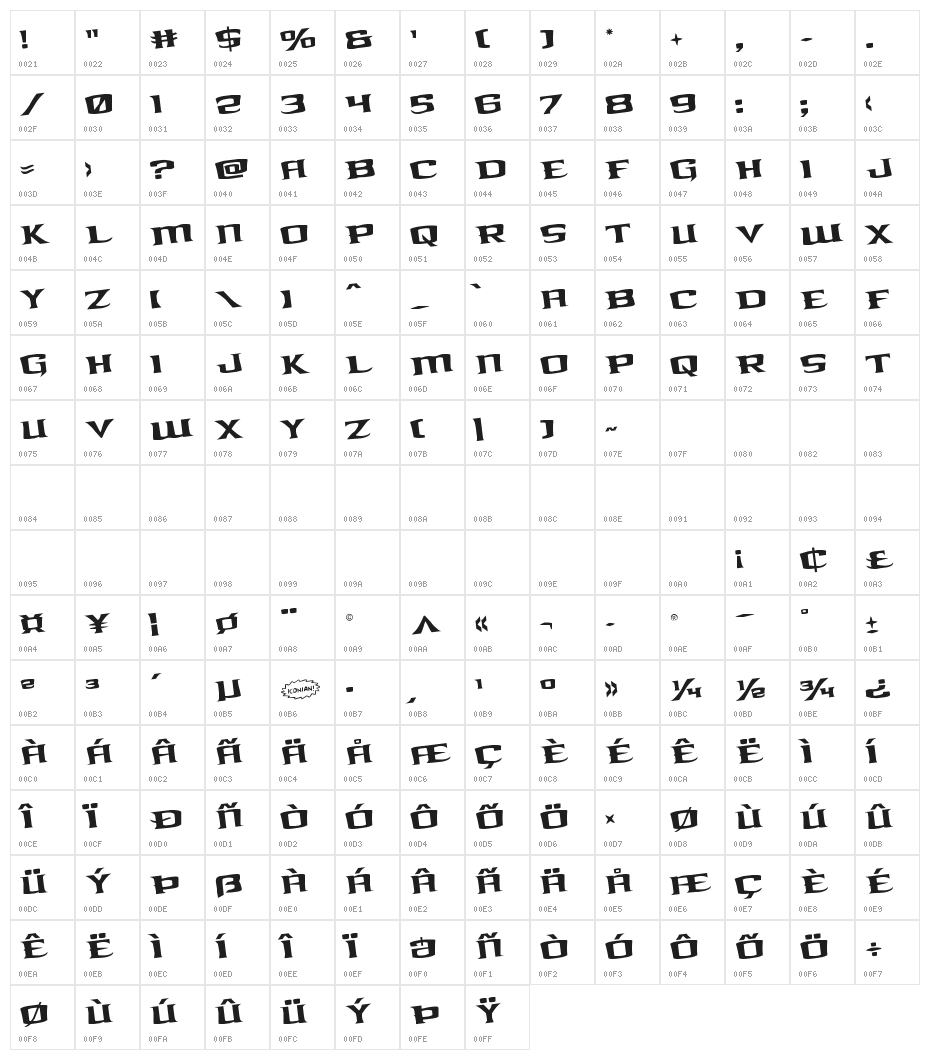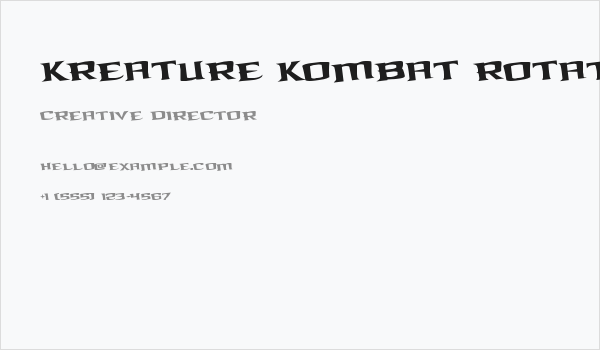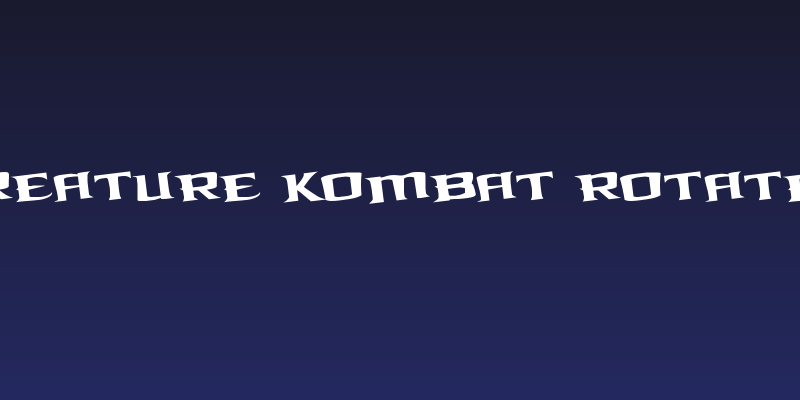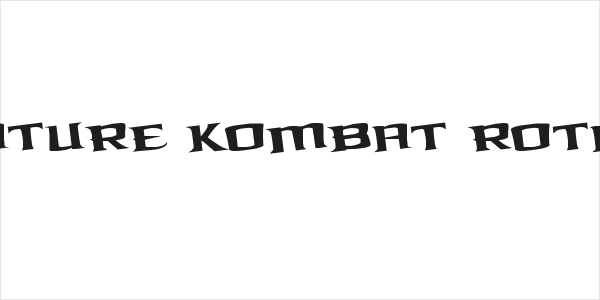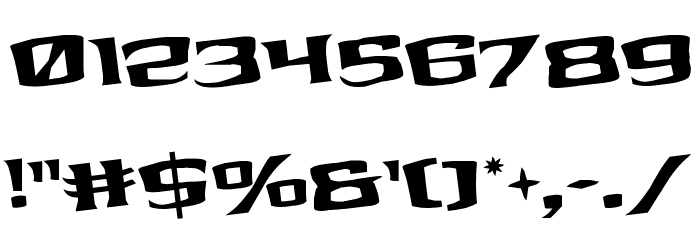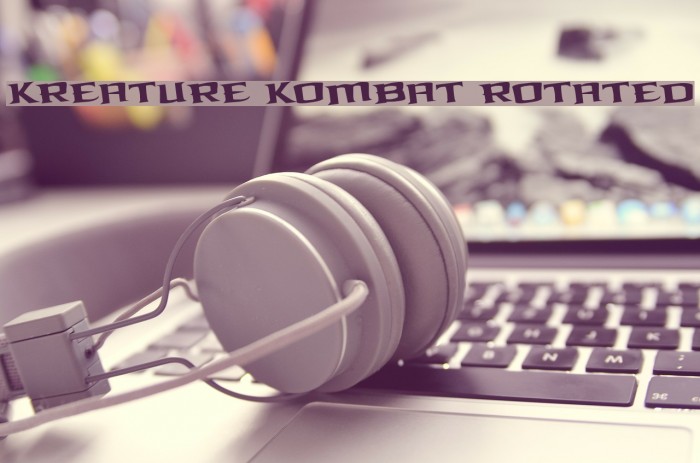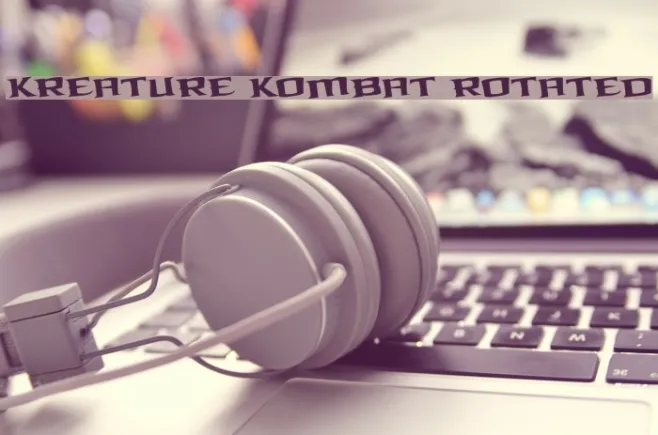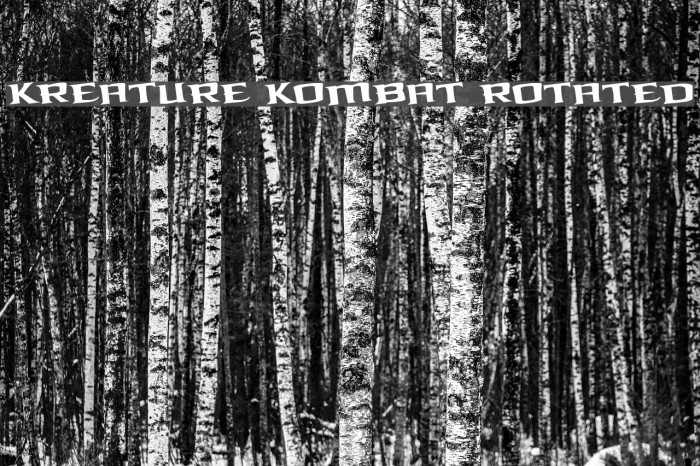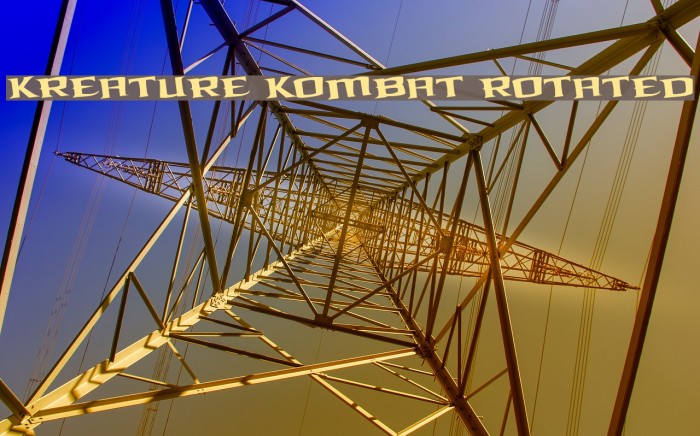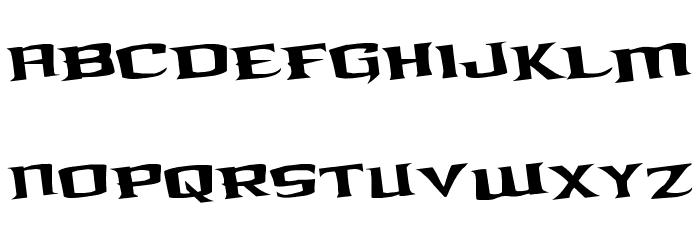
Kreature Kombat Rotated Font
| Estilo general | Modern, Aggressive |
| Proyectos propuestos | Ideal for video game titles, movie posters, sports team logos, or any project requiring a strong, impactful typeface. |